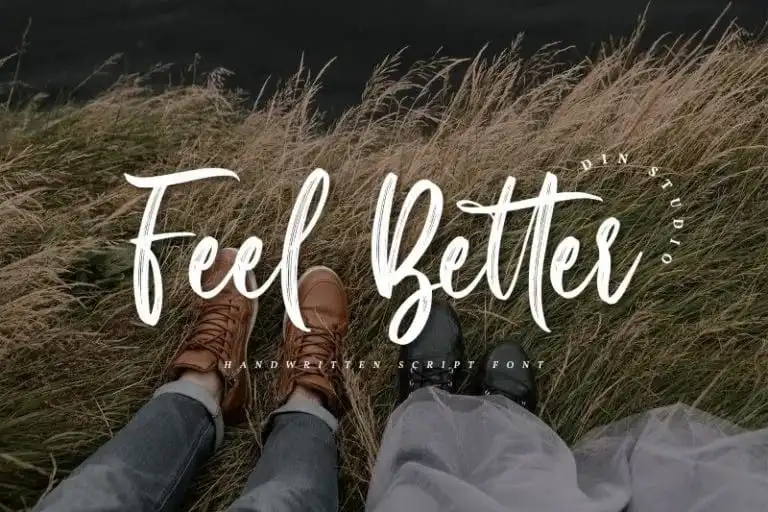
A Feel Better Brush Font é uma elegante e delicada fonte brush script criada por Din Studio. Ela captura a essência de uma escrita feita à mão, trazendo ao seu projeto um ar de graça e pomposidade. Esta fonte brilha perfeitamente em logotipos, branding e frases motivacionais. Ideal para qualquer projeto profissional que busque um toque especial, ela é a escolha certa para tornar suas criações mais únicas e belas. Não importa se você está criando uma marca digital ou apenas quer dar um ar de elegância à sua impressão em papel, esta font oferece o que há de melhor no mundo do design. Experimente Feel Better Brush Font e veja como ele pode tornar seu próximo projeto ainda mais atraente.